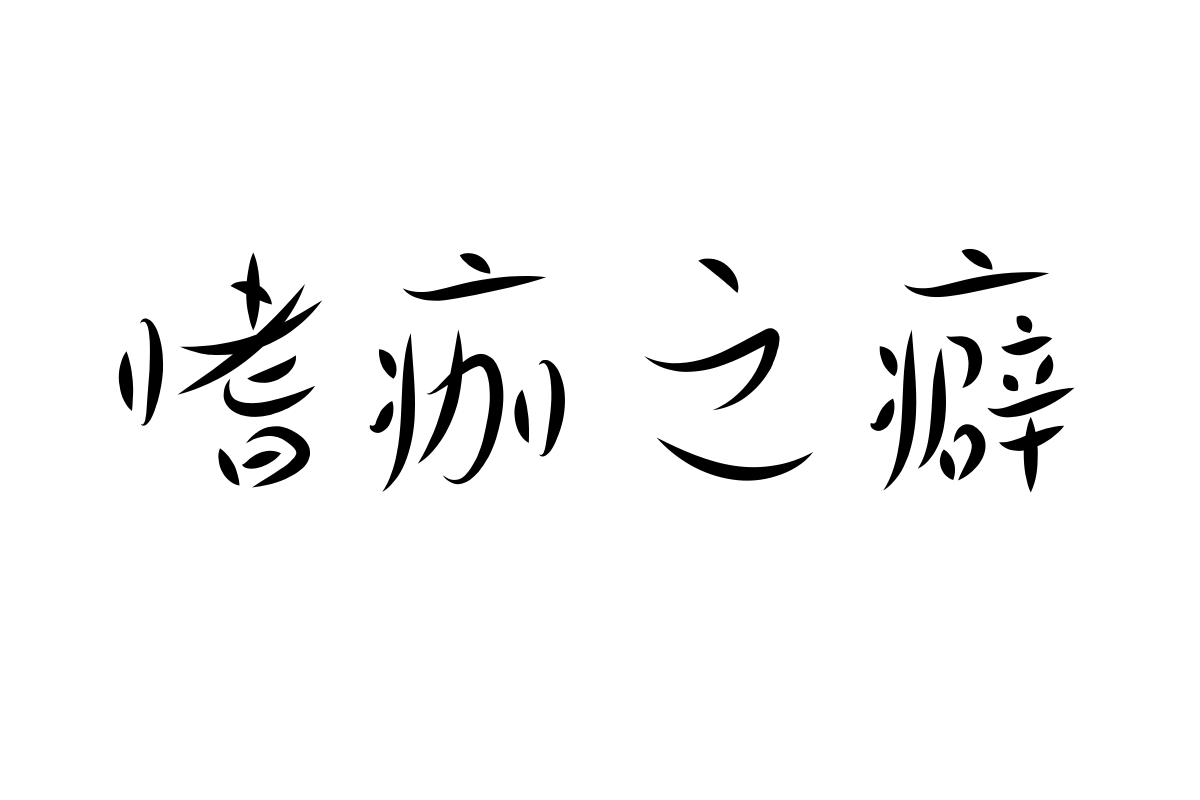
汉仪柳飘飘繁是一款具有独特韵味的字体,其笔画流畅,字形优美。这款字体采用了传统的书法风格,线条粗细适中,既有力度又有柔美。它的字体结构紧凑,每个字都像是精心雕琢出来的艺术品,给人以美的享受。
在设计上,汉仪柳飘飘繁注重细节,每一个笔画都经过精心设计,使得整体效果更加和谐统一。它的字体大小可调节,适合不同场合的使用需求,无论是用于标题、正文还是装饰性文字,都能展现出独特的魅力。
总的来说,汉仪柳飘飘繁是一款非常实用且美观的字体,适合用于各种需要展示个性和艺术气息的场合,如广告设计、书籍封面、海报等。